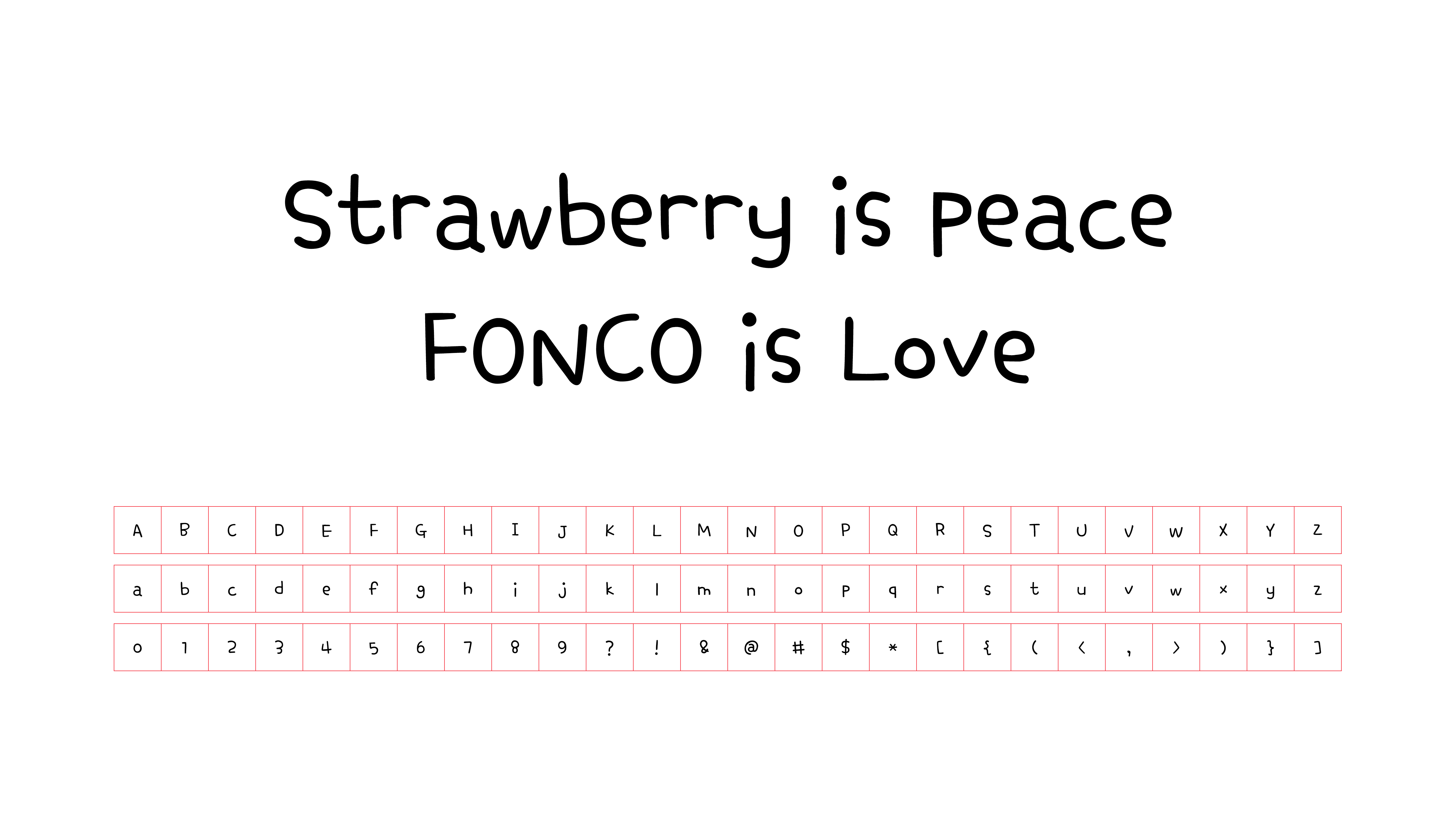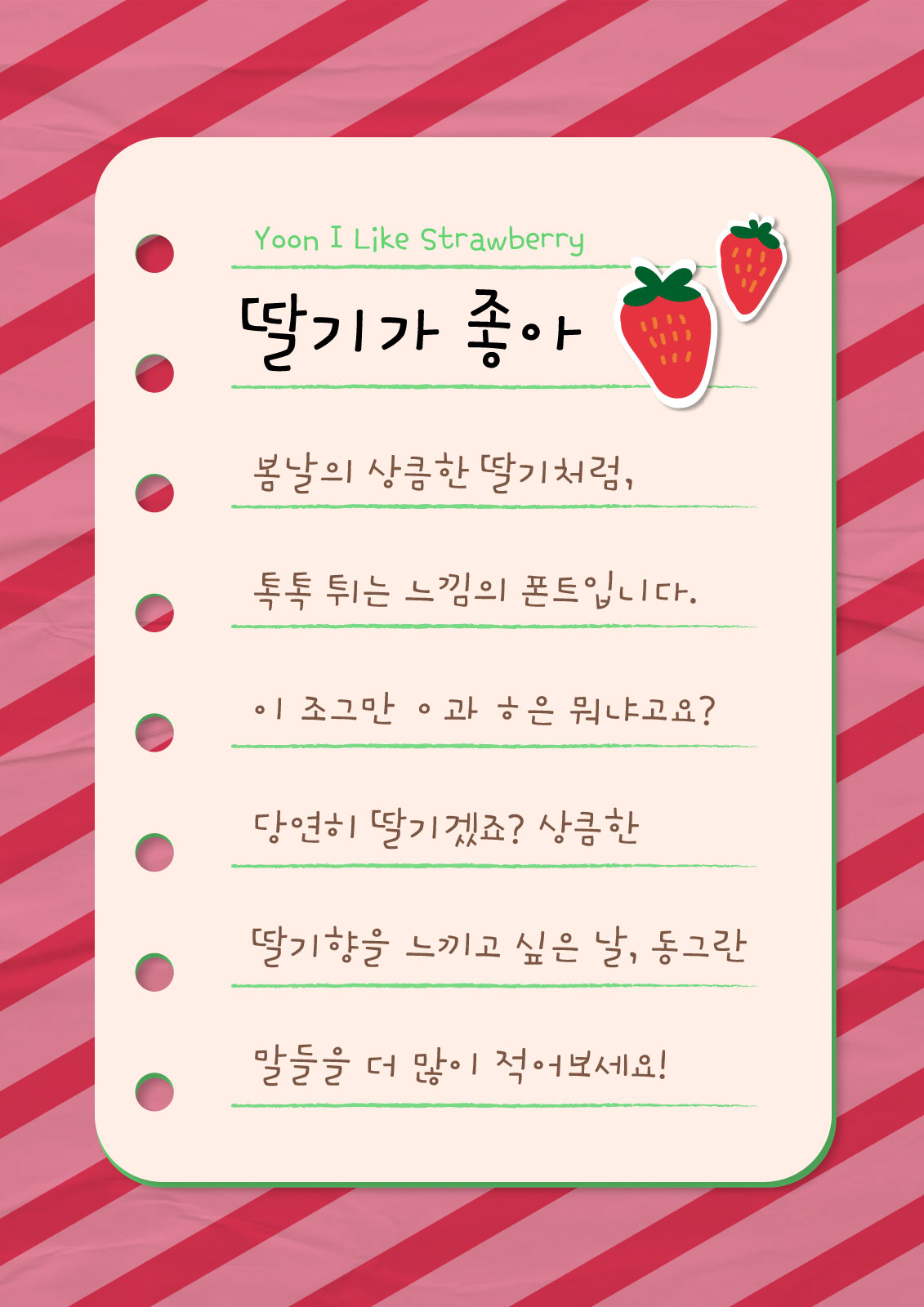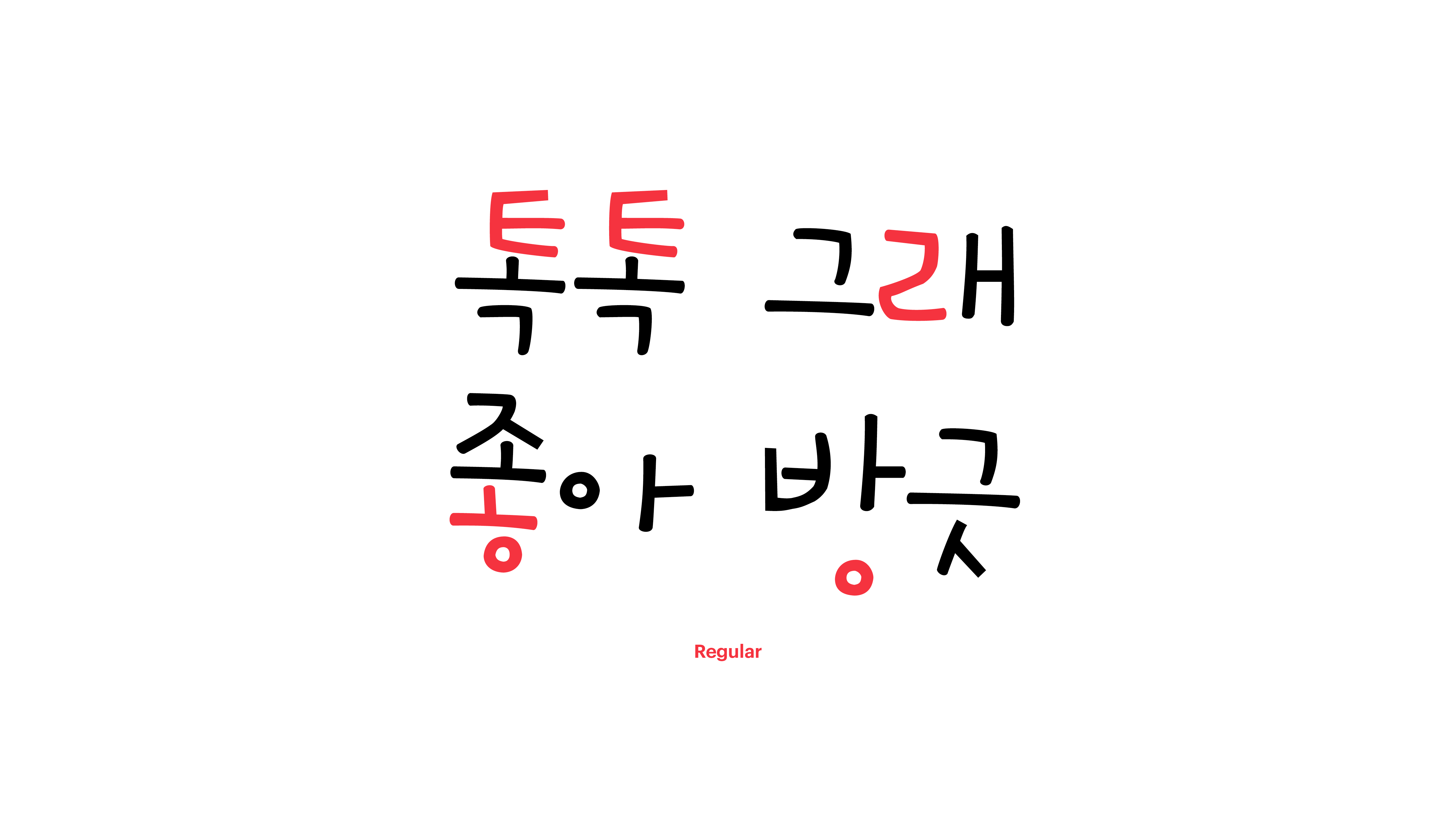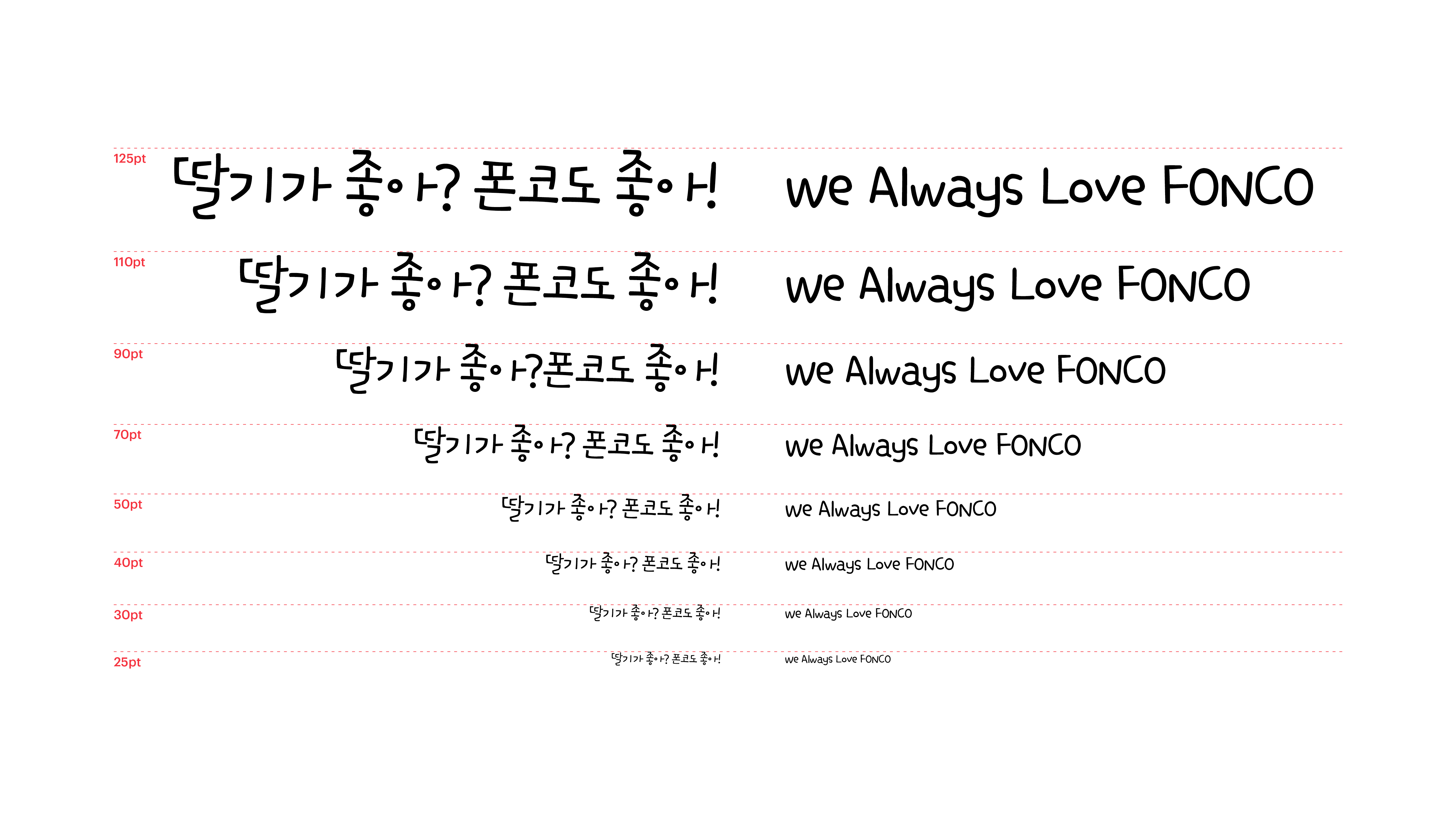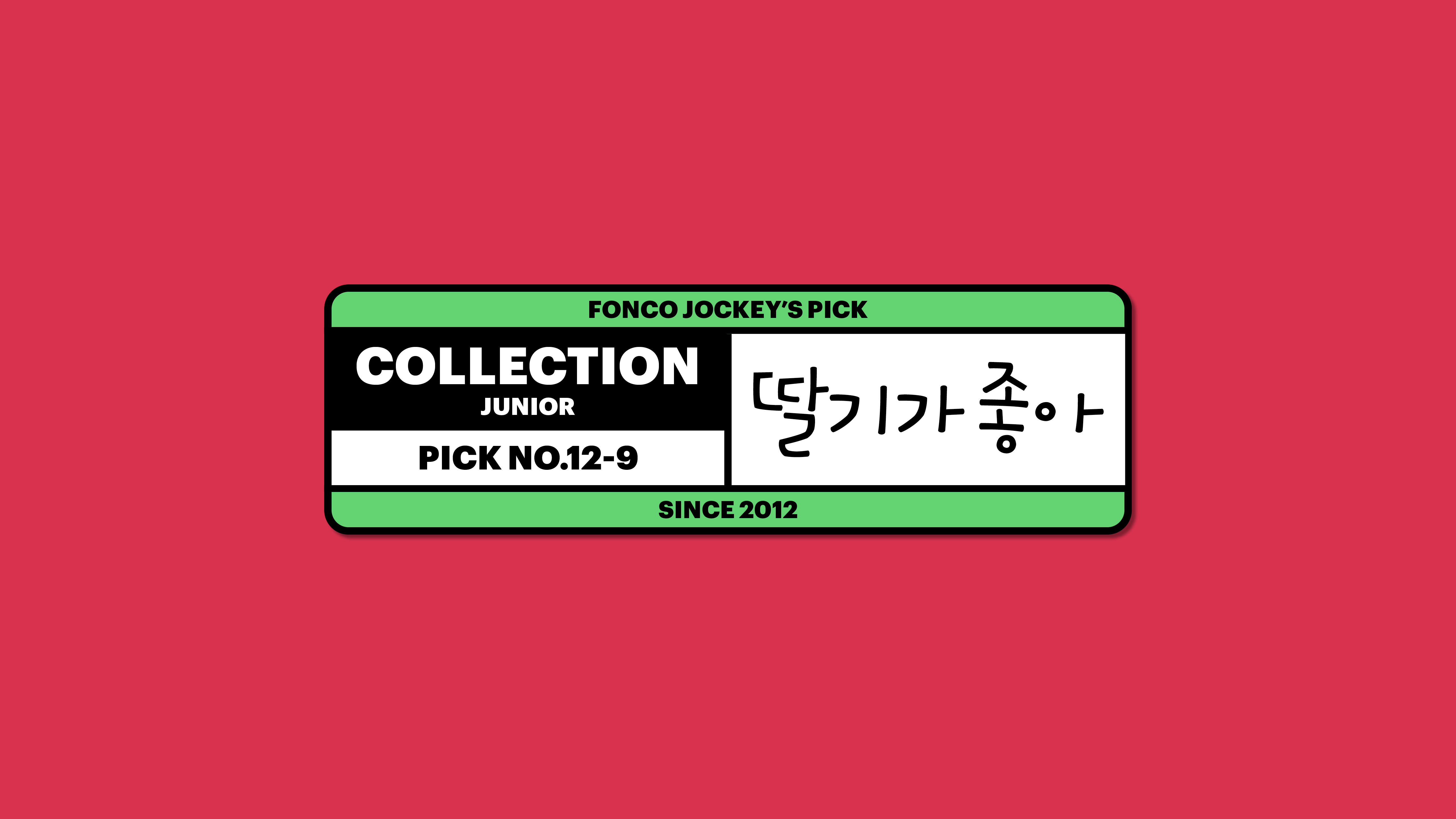
딸기가좋아
Yoon 딸기가좋아
봄날의 상큼한 딸기처럼, 톡톡 튀는 느낌의 폰트입니다. 특히 ㄱ과 ㄹ의 표현에서 멋을 좀 부려봤어요. 귀여운 넝쿨 같지 않나요? 그럼 이 조그만 ㅇ과 ㅎ은 뭐냐고요? 당연히 딸기겠죠? 상큼한 딸기향을 느끼고 싶은 날, 동그란 말들을 더 많이 적어보세요!